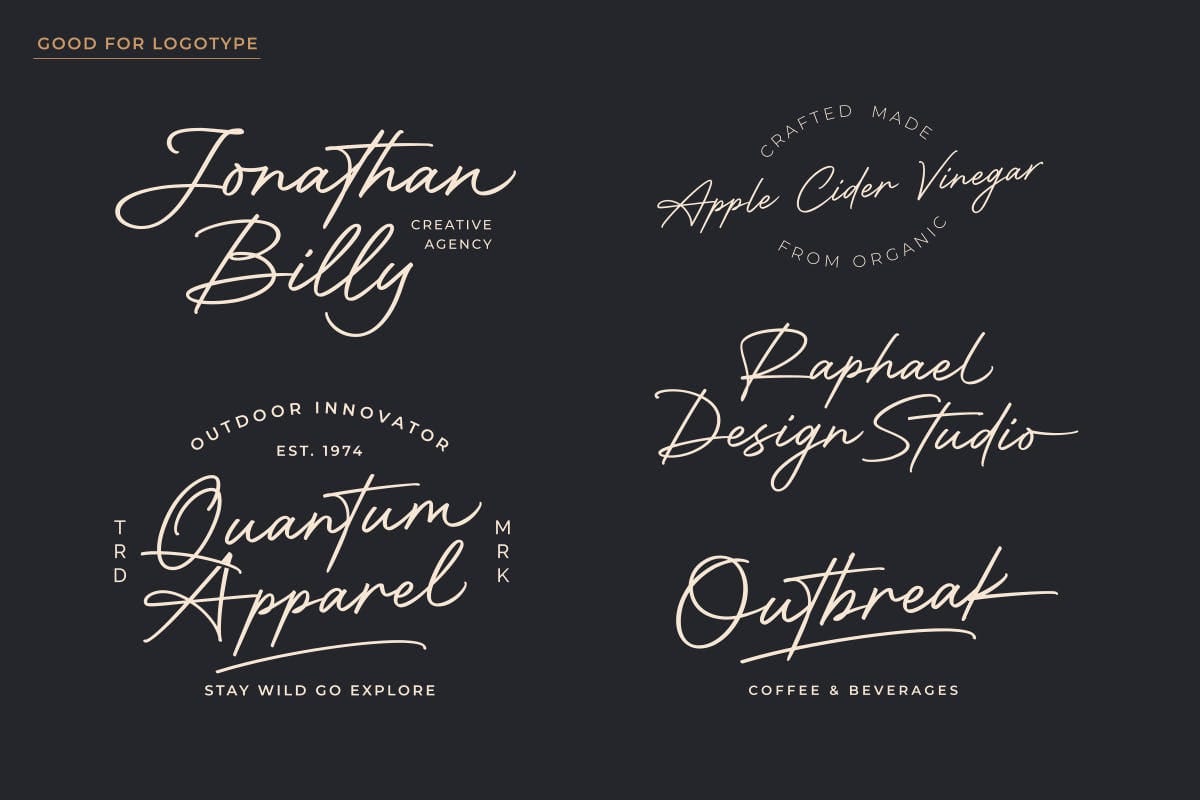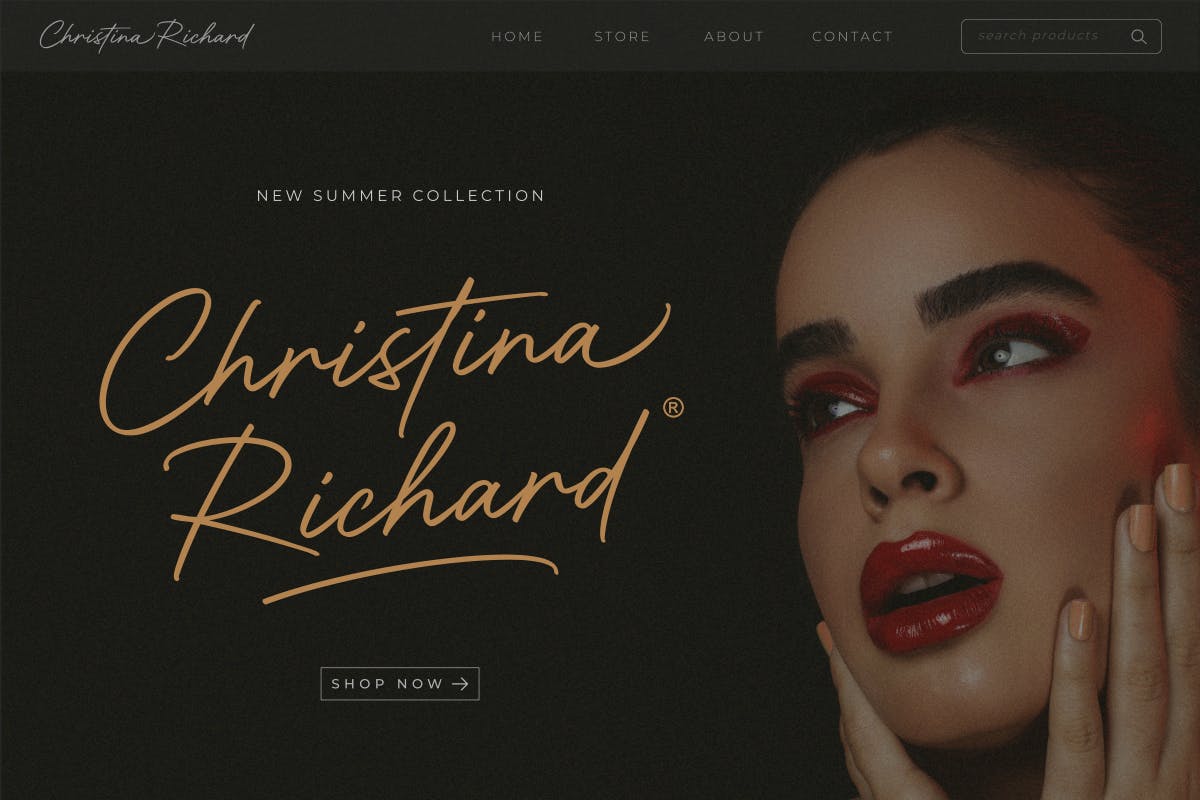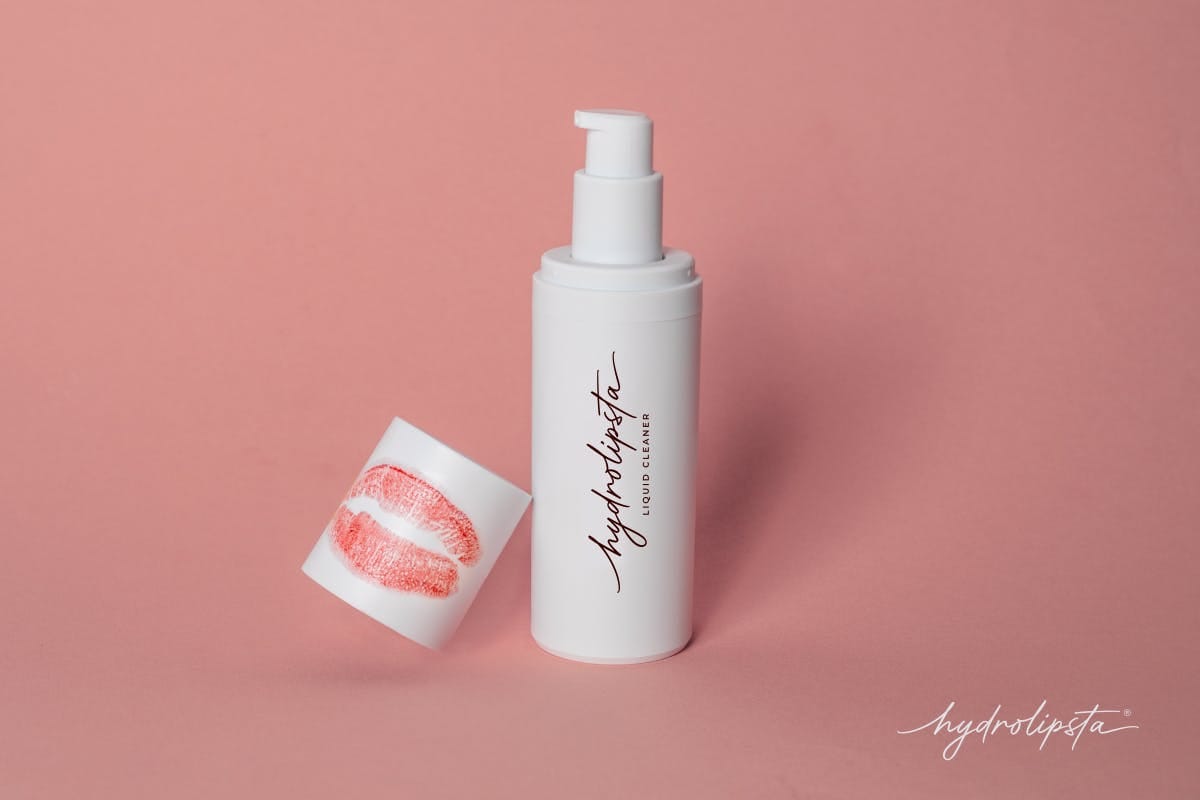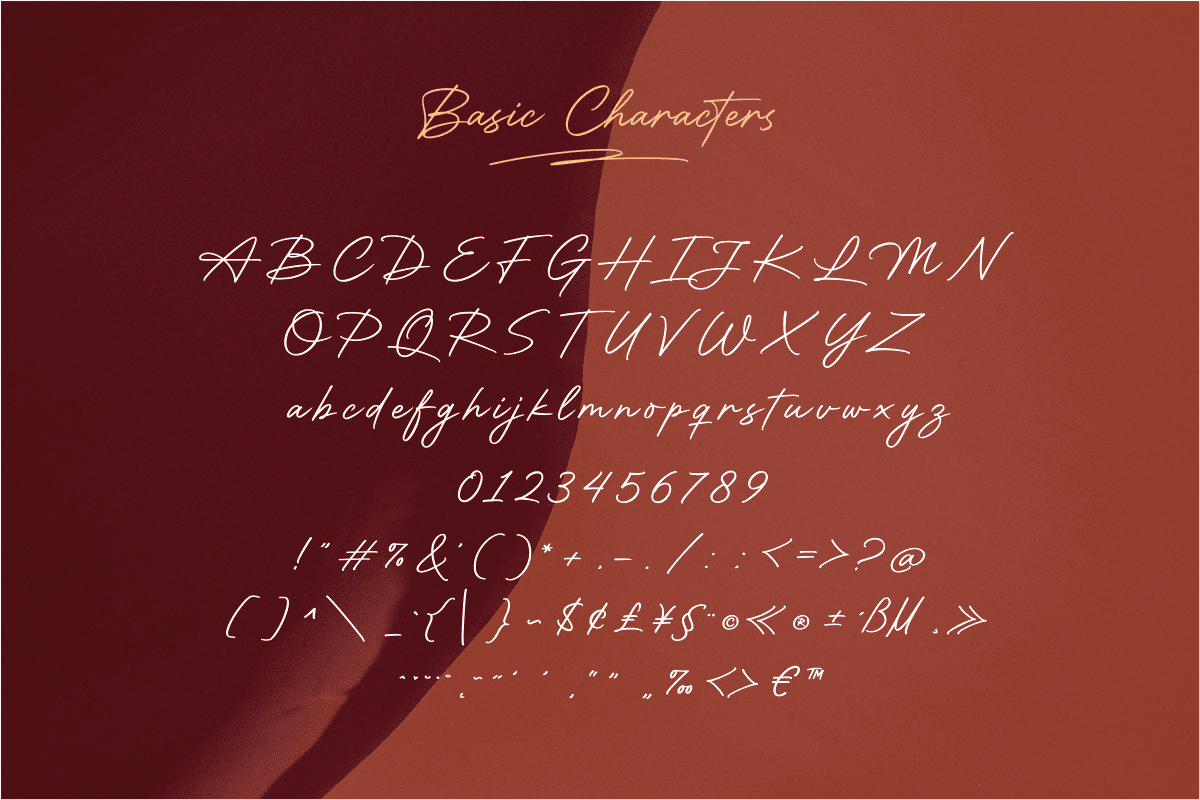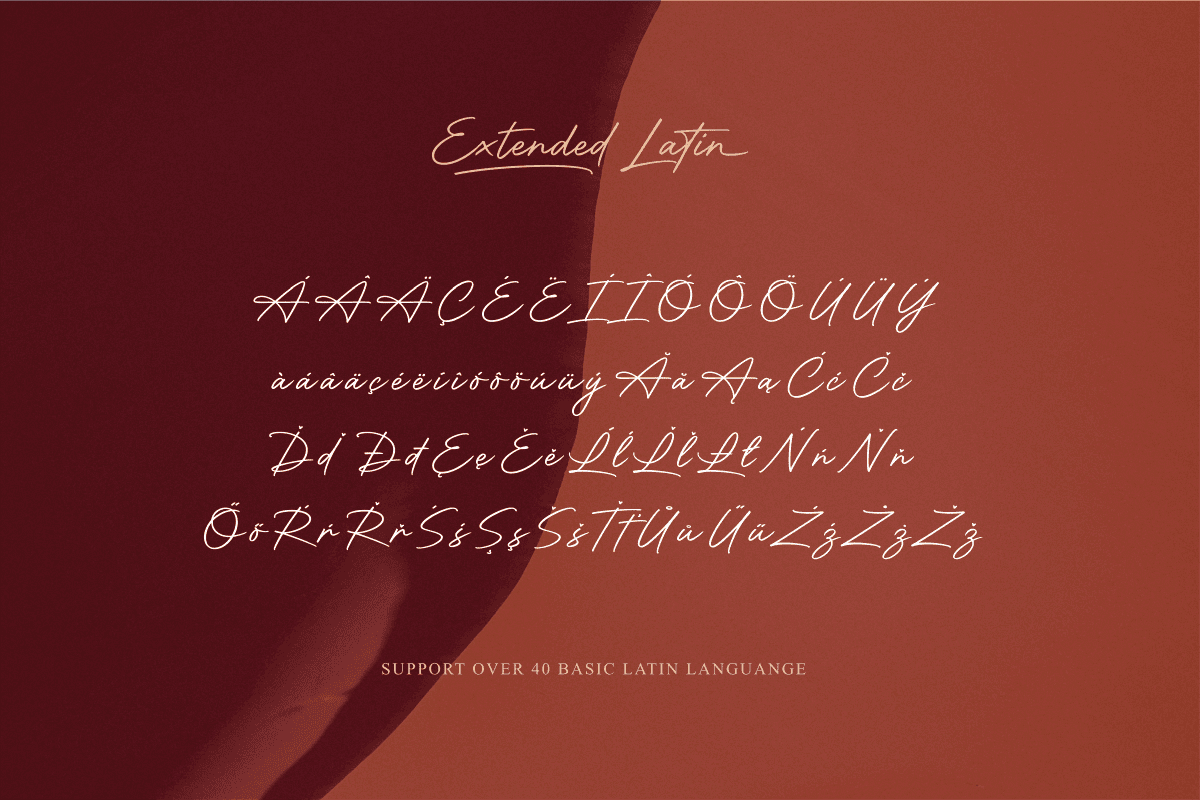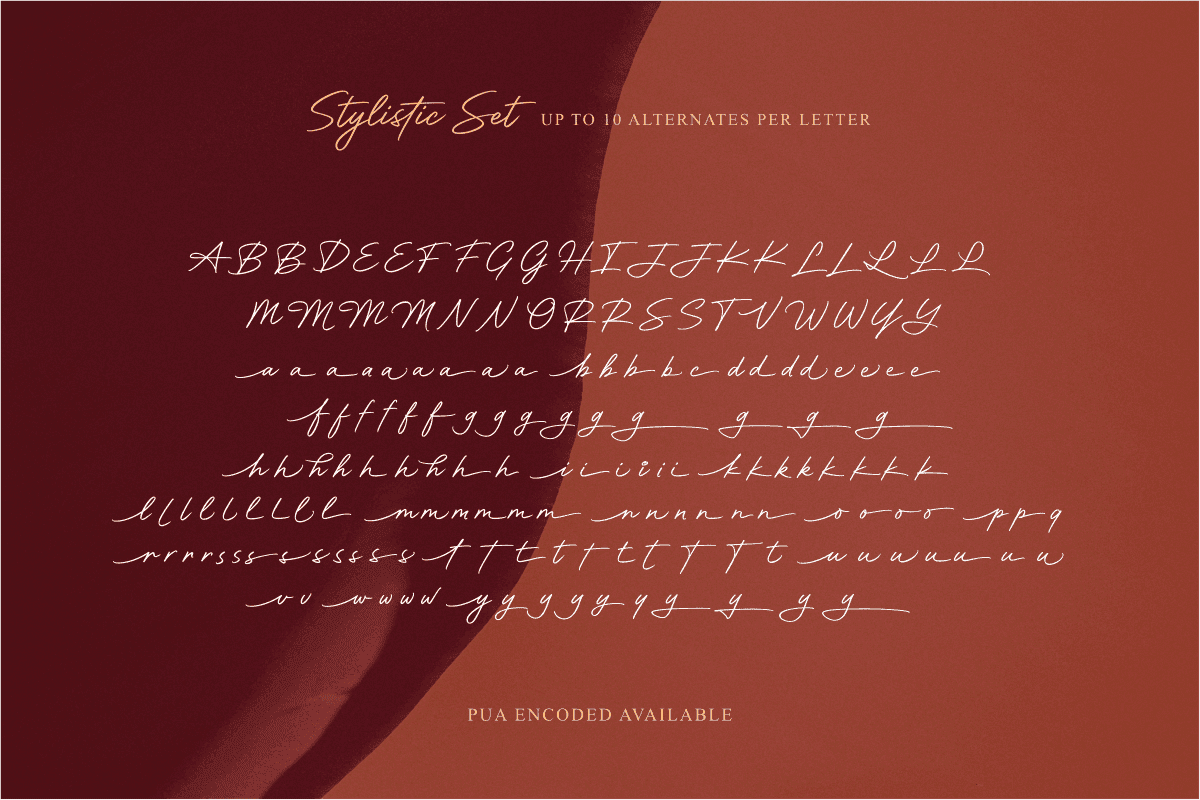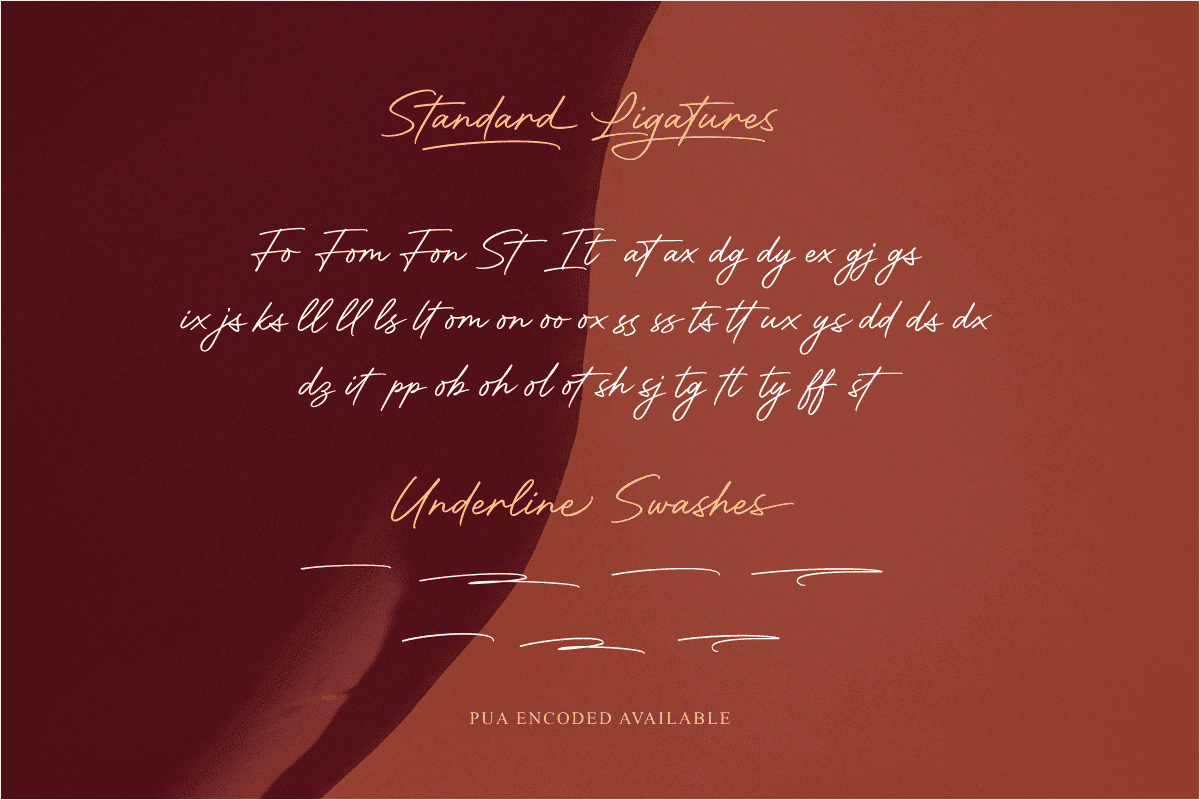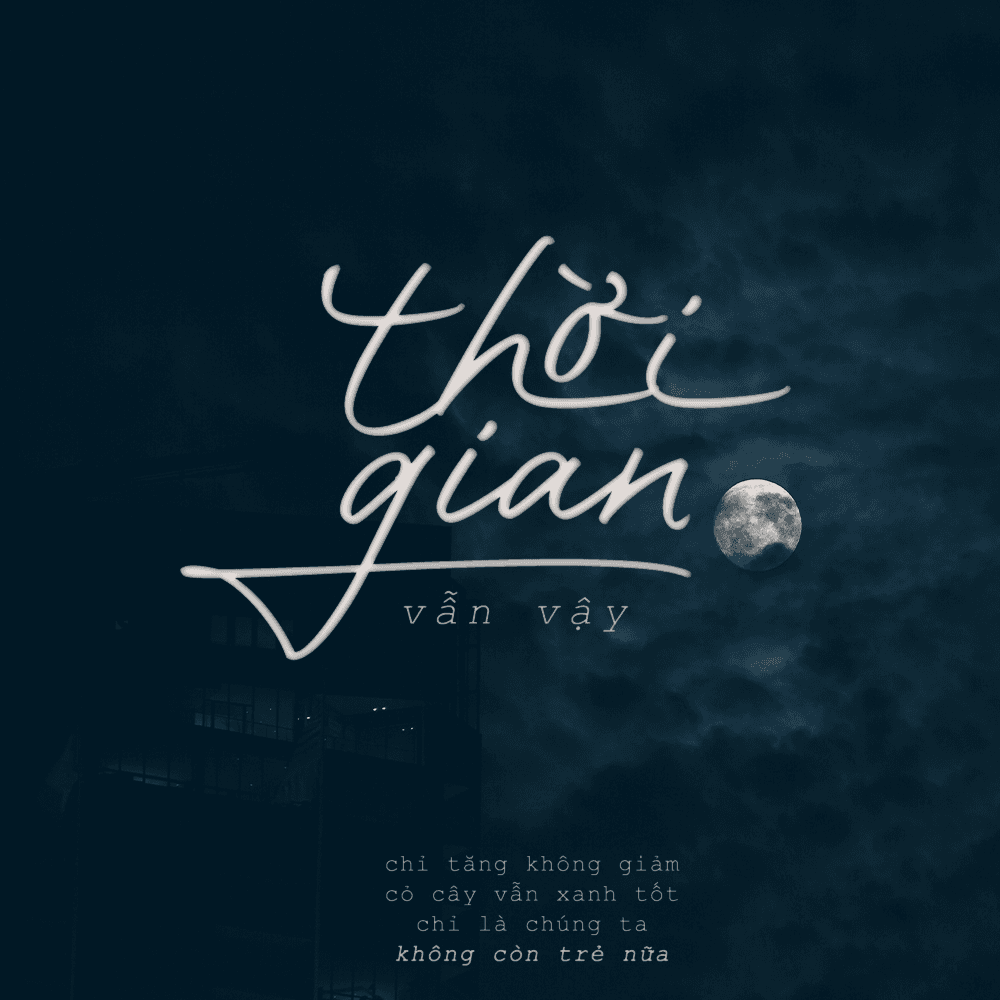
Motherland Signature Việt Hóa – Font viết tay
Giới thiệu Motherland Signature. Một font chữ viết tay quyến rũ để thêm thiết kế kiểu chữ của bạn trông hiện đại nhưng thanh lịch. Font chữ này sẽ được sử dụng tốt cho Danh thiếp, Sản phẩm Mỹ phẩm, Quảng cáo Áp phích, Biểu trưng, cho Tiêu đề Phim hoặc Sách và nhiều hơn nữa.